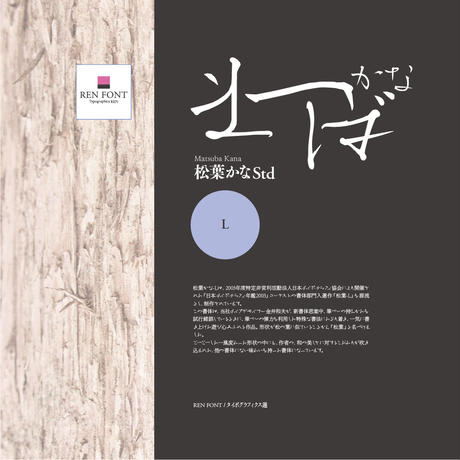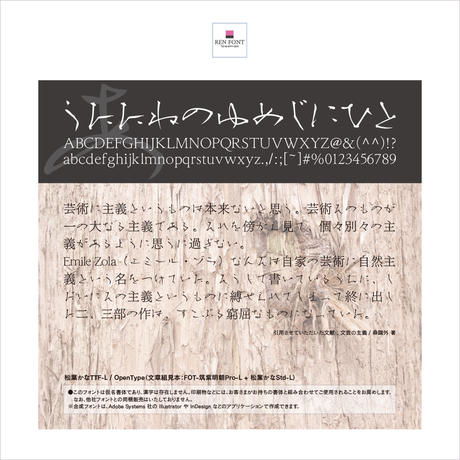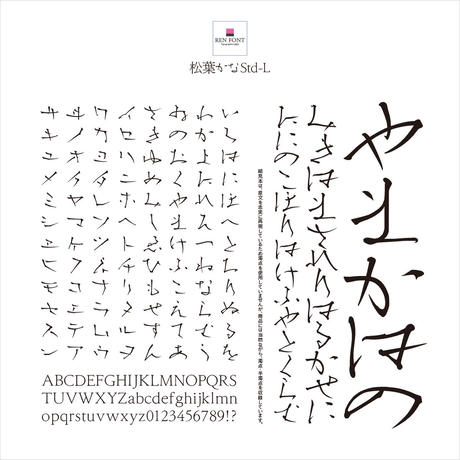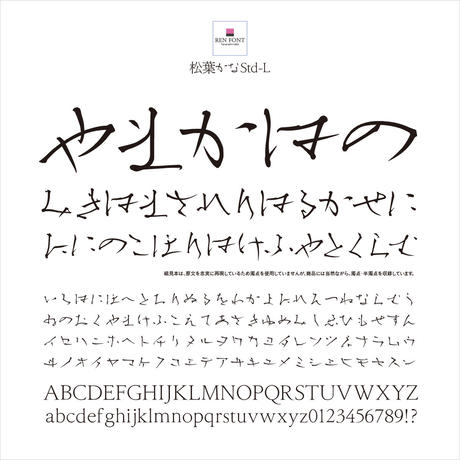
松葉かな-Lの各書体は、2003年度特定非営利活動法人日本タイポグラフィ協会により開催された「日本タイポグラフィ年鑑2003」コンテストの書体部門入選作「松葉-L」を源流とし、制作されています。
松の葉をモチーフとした弊社タイプデザイナー金井和夫の遊び心あふれる作品。他の書体にない鋭さと和風を感じさせる書体になっています。
平仮名、片仮名、欧文、記号類を収録しています。
収録の各字種の特徴としては、以下のような特徴を備えています。
□仮名 / 仮名は文章の雰囲気を決める重要要素。細めの明朝等の書体と組み合わせることで、デザインの雰囲気を一変させます。